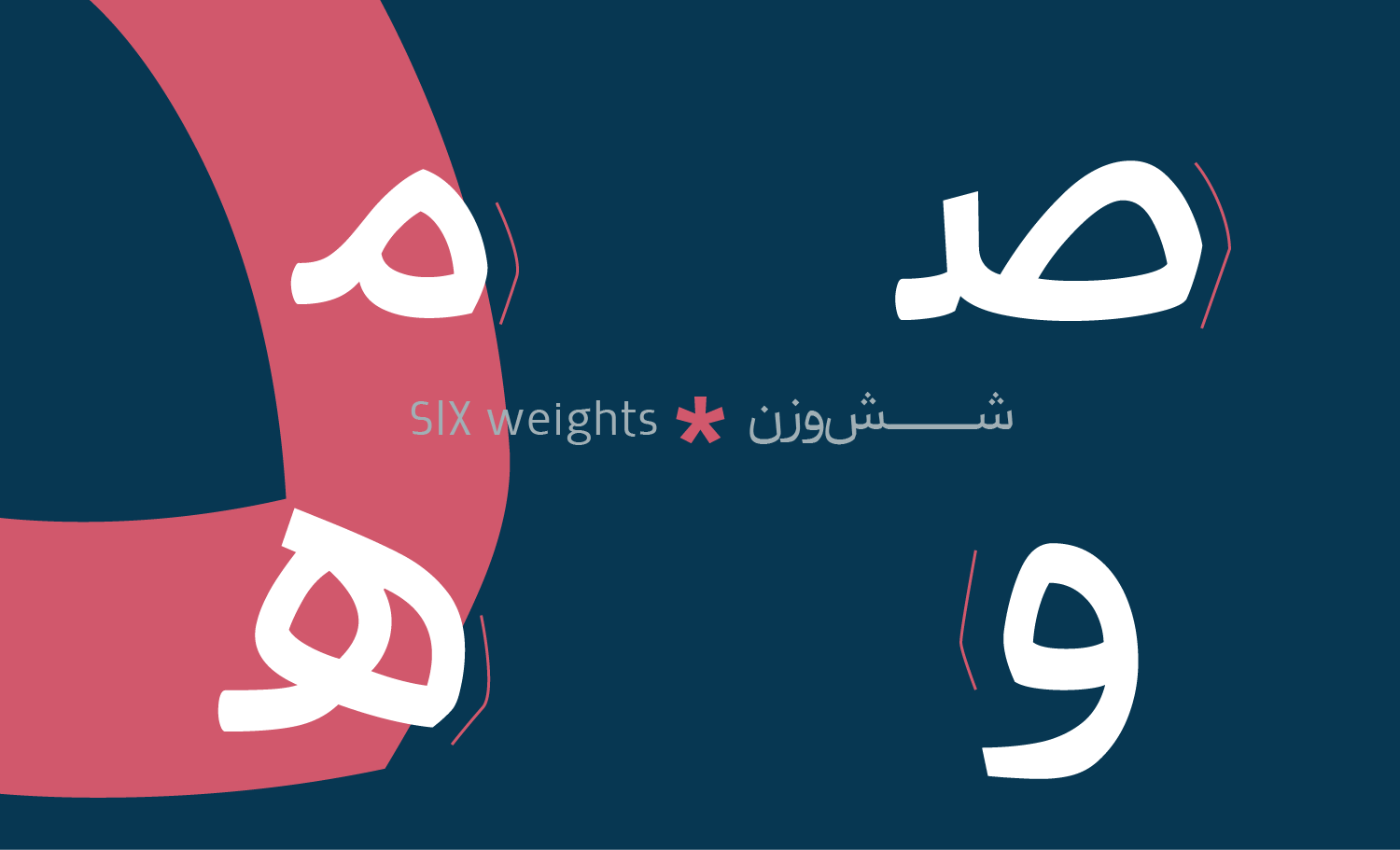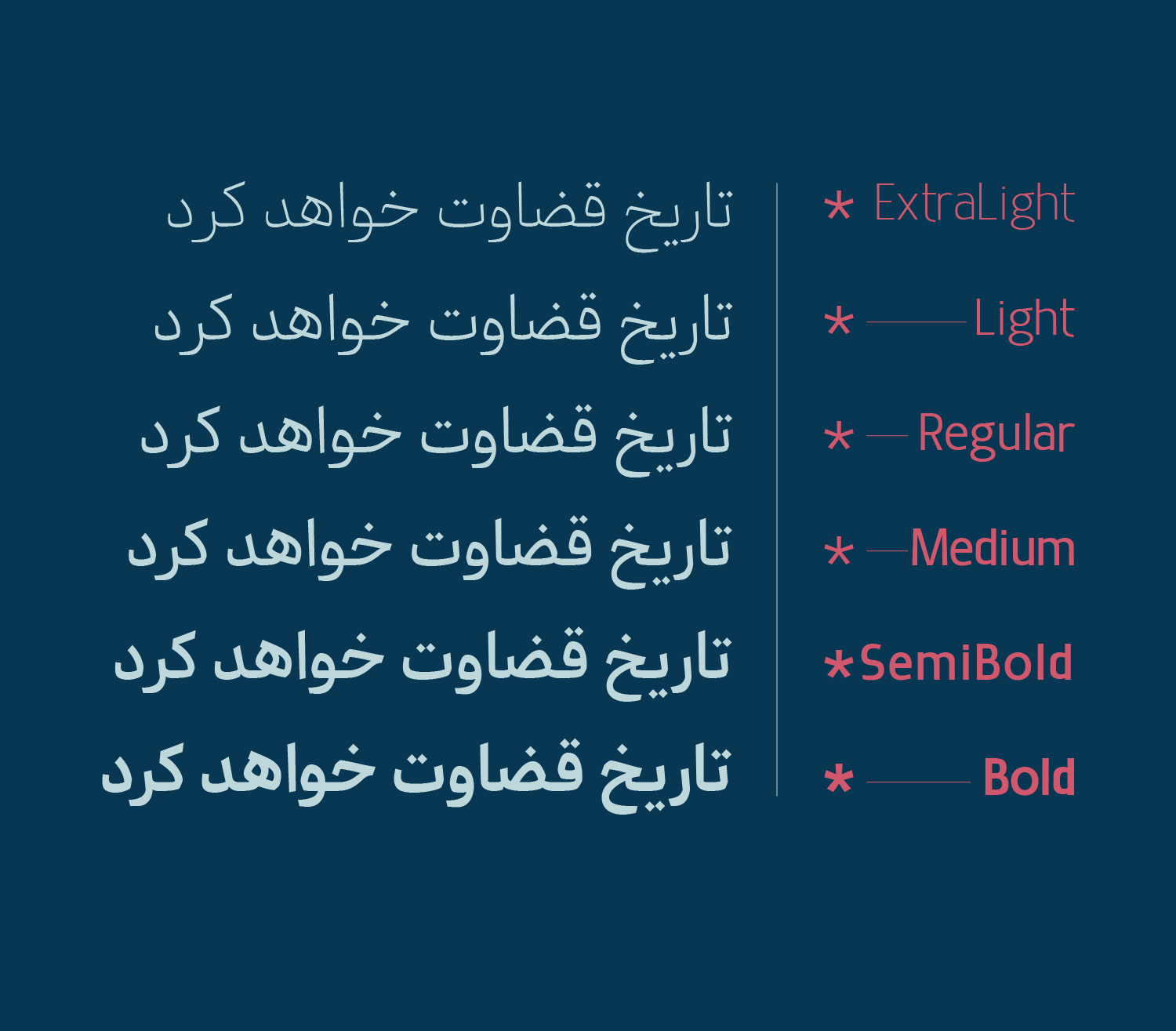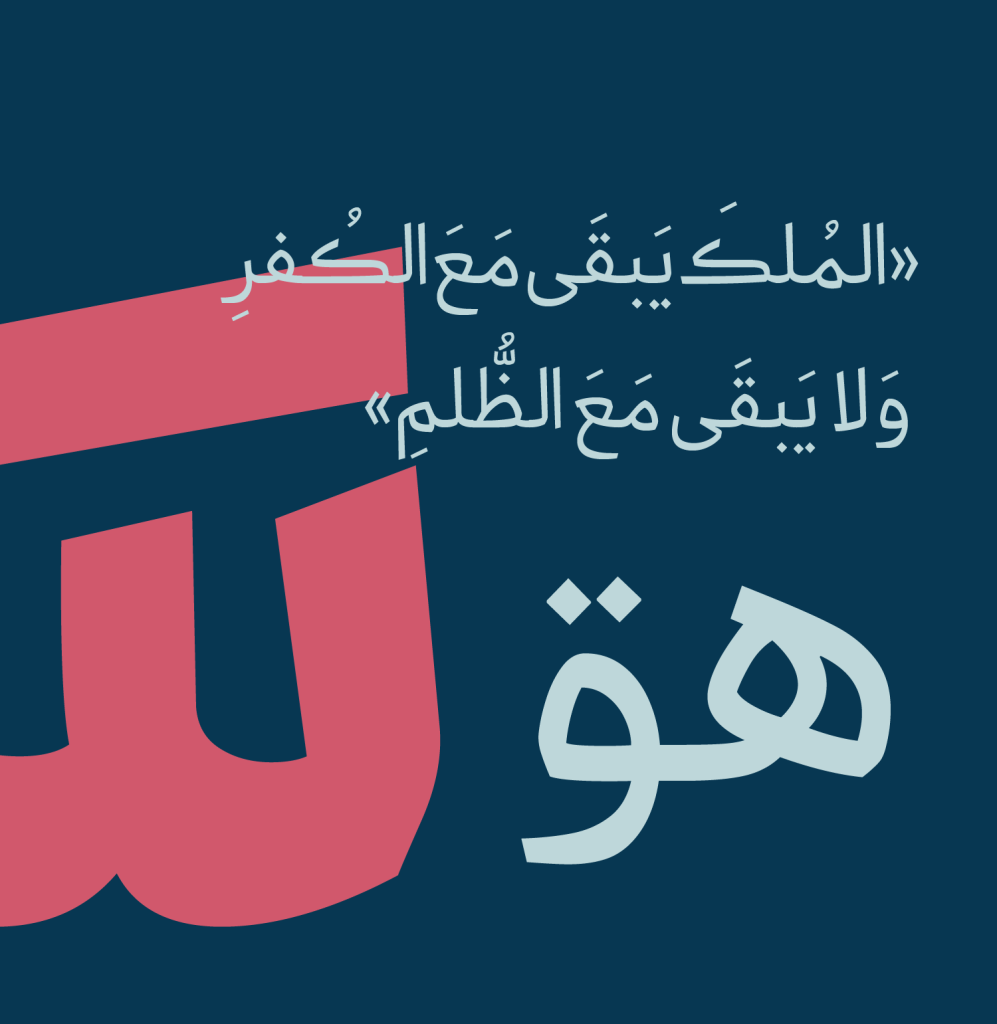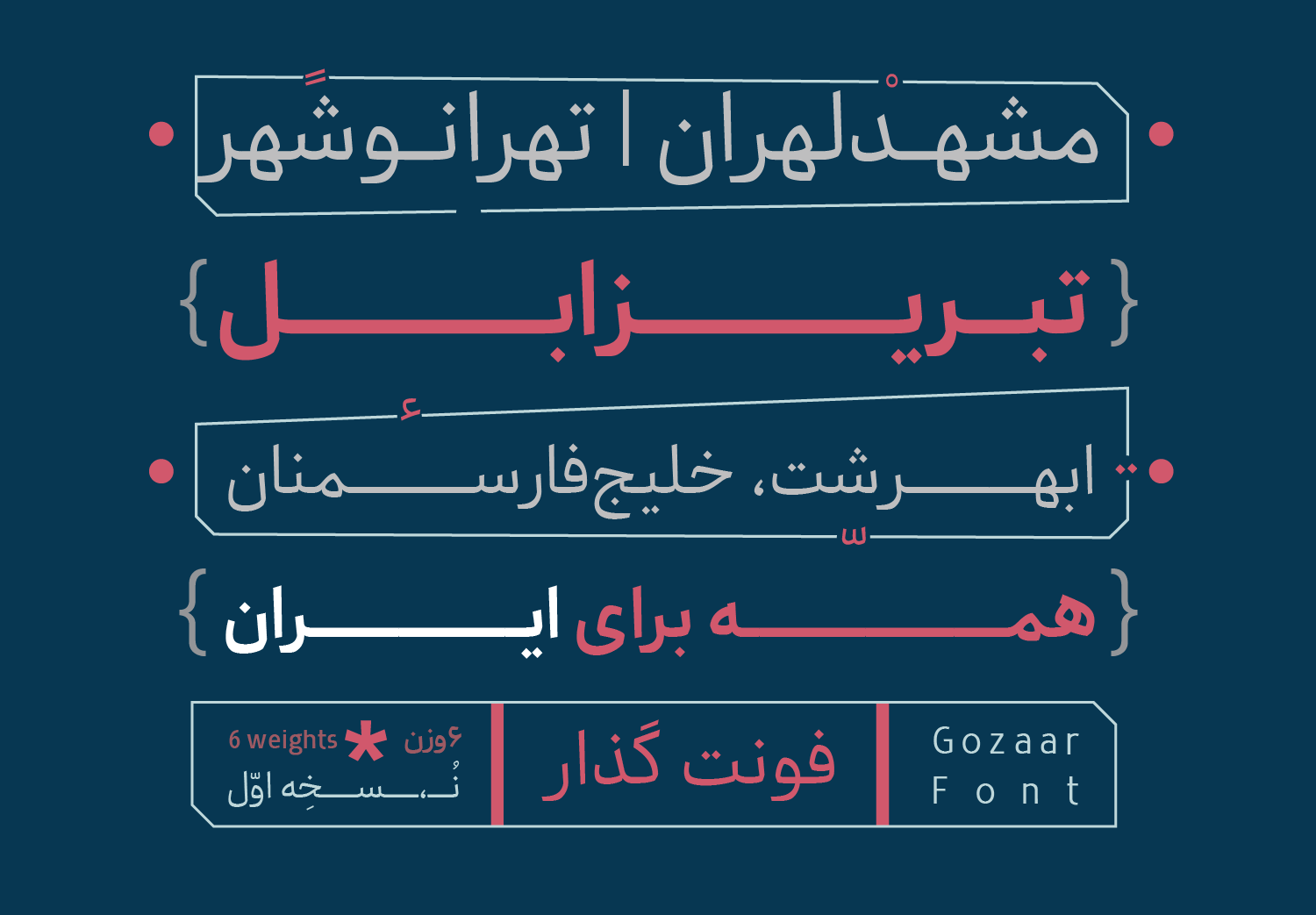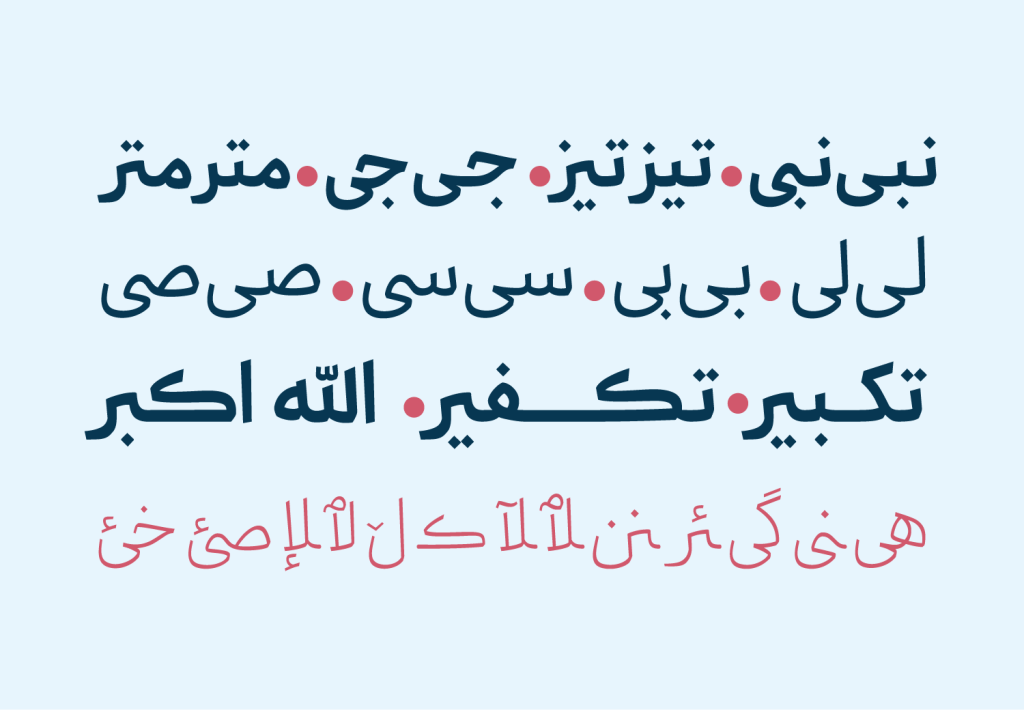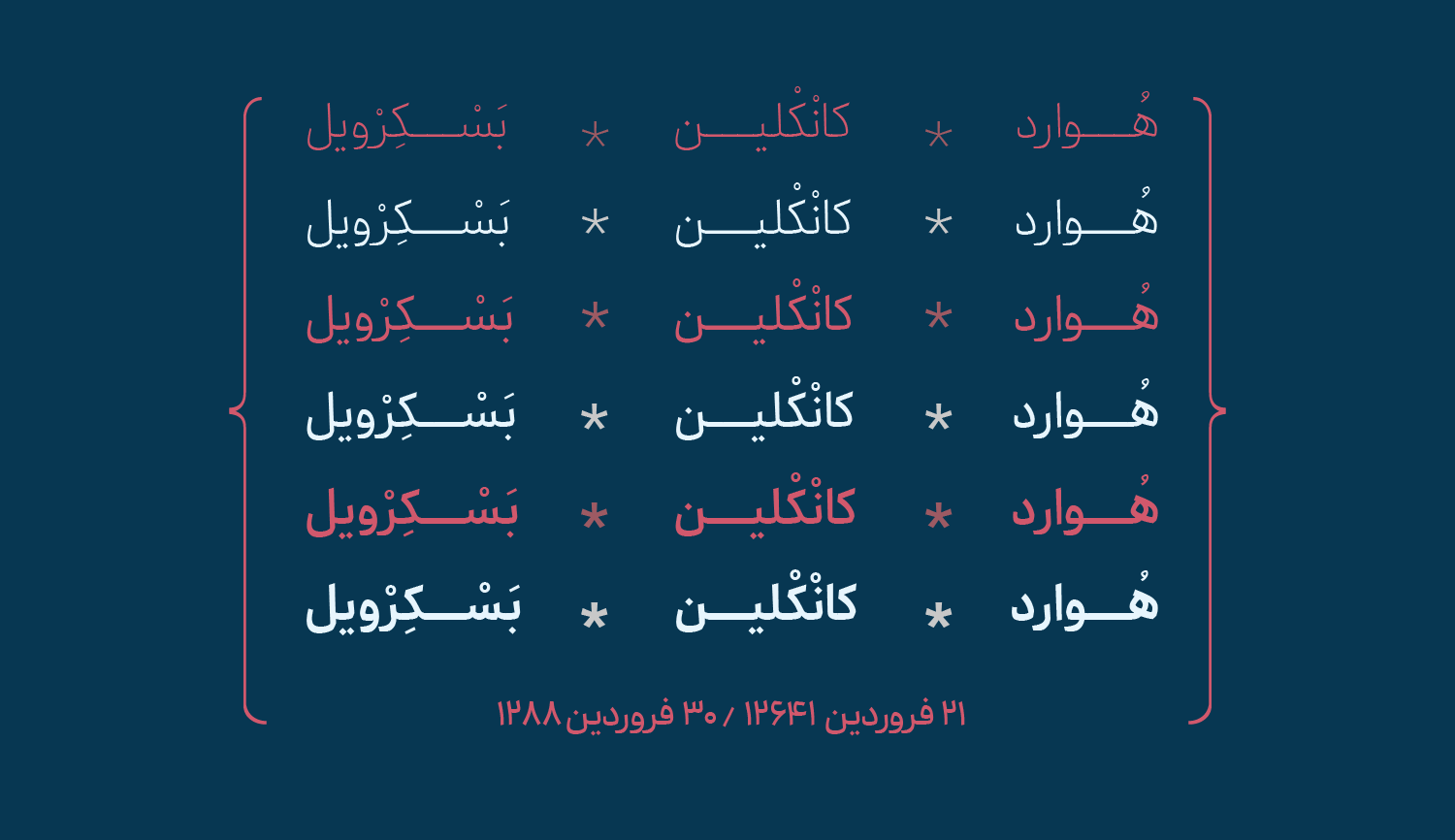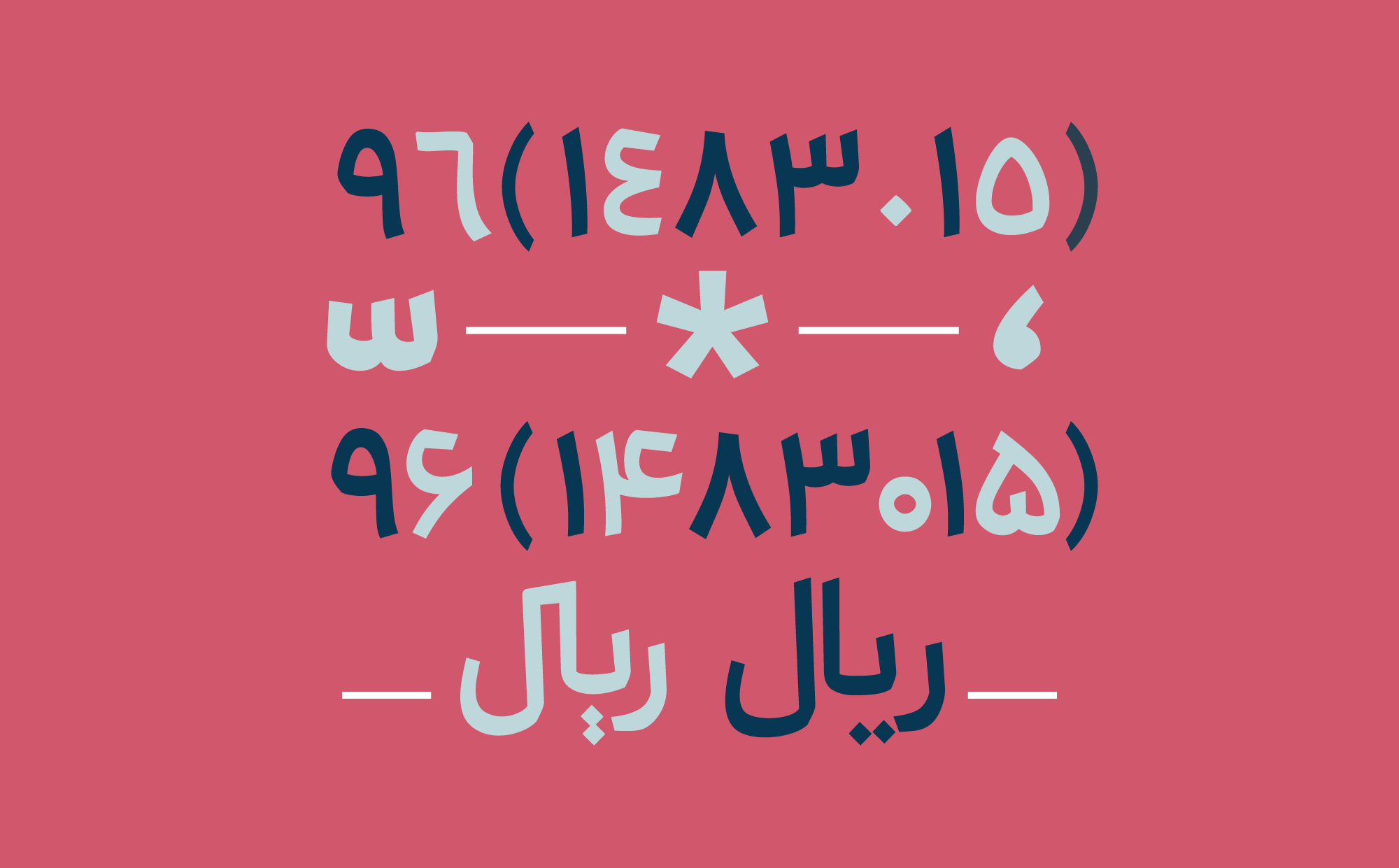
فونت گذار قلمی که هم ویژگی اصالت را از خانواده نسخ و روحیه امروزی و مدرن و نو را از خط سنس ارث بری کرده است . البته این قلم در مجموع از خانواده نسخ به حساب می آید.
فونت گذار – نتیجه تلاش 2 ساله طراح آن
فونت گذار قلمی به طراحی مهرداد نوتاش و نتیجه تلاش دوساله ای که در این مسیر با چالش ها و مشکلاتی بسیار همراه بوده و سرانجام موفق و پیروزمندانه با تولید قلمی زیبا همراه شده است. این زمان سپری شده در رفع مشکلات و …. نشان از توجه و تمرکز جهت رفع و افزایش دقت برای تولید محصولی بوده که به ظرافت های طراحی در آن توجه زیادی گشته است.
تایپ فیس بنیاد کودک از نقطه نظر شباهت هم خانوادگی و سبک طراحی بسیار به این تایپ فیس نزدیک است که در عین رعایت رسم الخط نسخ تا حدی هم به فونت‌های دسته سنس همانند گذار شباهت دارد.
اگر بخواهیم قدیری از چالش های 2 ساله را برای شما دوستان بیان کنیم می توان به ایجاد وجه تمایز با سایر فونت‌ها و همچنین حفظ زیبایی ، علیرغم کاربردی بودن آن اشاره نمود .
این تایپ فیس زیبا مناسب برای متنون کتاب ها و مطبوعات و همچنین طراحی وبسایت و نرم افزارهایی دنیای وب است که می‌خواهند حال و هوای اصیل و فرهنگی داشته باشند. دارا بودن اصالت و درعین حال به روز و امروزی بودن از ویژگی های اصلی این تایپ فیس زیبا به شمار می رود.
ابتدای راه برای گذار و منتظر به روز رسانی های بعدی
این قلم در ابتدای راه با نسخه اولیه ای در ۶ وزن : (ExtraLight-Regular-Medium-Bold-Semibold-Bold)
تمامی حروف و مفردات با حفظ استقلال خود دارای فرم های یکپارچه هستند که رفتارهای نمایشی در وزن های بالا بیشتر به چشم می خورد . اما در ادامه این مسیر به دنبال ارتقاء و به روز رسانی های بعدی از این قلم زیبا هستیم امیدواریم با مشاهده تصاویر نمونه از زیبایی ها و ظرافت های طراحی گذار نهایت استفاده را ببرید .
زبان‌های پشتیبانی شده :
فارسی , انگلیسی , اُردو , عربی , کوردی
6 وزن